Sonderalphabete
Wenn das gewöhnliche Alphabet nicht ausreicht, entstehen Sonderschriften: Punkte und Striche für die Telegrafie, Kurzzeichen für den schnellen Mitschrieb, Q-Gruppen für die Funkpraxis. Schriften, die Sprache komprimieren oder über große Entfernungen tragen.
Nach der ersten erfolgreichen transatlantischen Telegrafie war die Entwicklung einer Funksprache folgerichtig. Im 2. Weltkrieg entstanden die Q-Gruppen — eine Kurznachrichtenvariante, die bis heute im Notfunk Bestand hat.
Um gesprochene Sprache direkt mitschreiben zu können, war es notwendig, Wörter und Buchstabenkombinationen durch grafische Kürzel zu ersetzen. So entstanden die Kurzschriften oder Stenografien — eigene Notationssysteme für eine eigene Aufgabe.
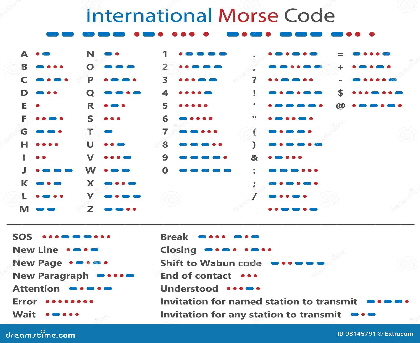
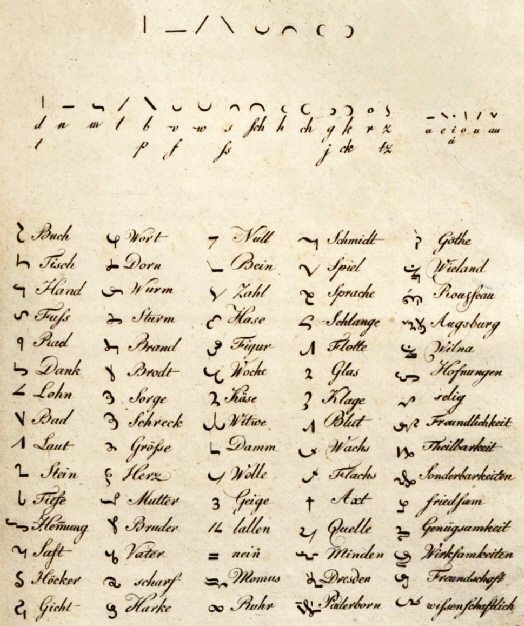Zeichen jenseits des Alphabets
Punkte, Striche und Kürzel
Tafel mit dem Morsealphabet
Ab 1837
Das Morsealphabet
Samuel Morse und Alfred Vail übersetzten das lateinische Alphabet in eine Reihenfolge aus kurzen und langen Signalen. Ob als elektrischer Impuls, Lichtblitz oder Klopfzeichen — das Morsealphabet ermöglichte erstmals die Übertragung von Sprache über fast jede Entfernung.
Historische Stenografie von Horstig, 1797
Um 1797
Stenografie
Schon im 18. Jahrhundert entwickelte Horstig ein Schnellschreibsystem für die deutsche Sprache. Spätere Kurzschriften wie Stolze-Schrey oder die Deutsche Einheitskurzschrift komprimieren Wörter zu eleganten Schleifen — schnell genug, um gesprochene Rede in Echtzeit zu Papier zu bringen.